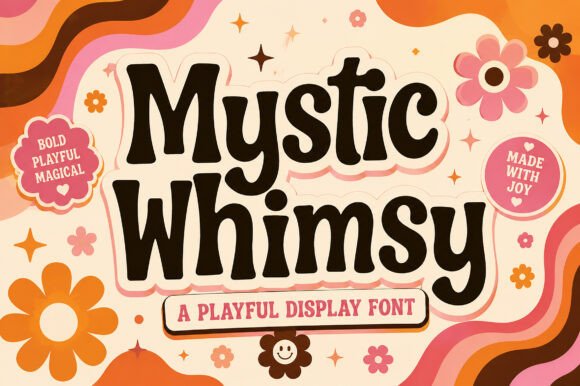
Mystic Whimsy
適切なデザイン要素を見つけるのは難しい場合がありますが、Mystic Whimsyは作品を即座に引き立てる優れたコレクションを提供します。
POD(オンデマンド印刷)製品、結婚式の招待状、またはソーシャルメディアのグラフィックを作成している場合でも、Mystic Whimsyは理想的です。